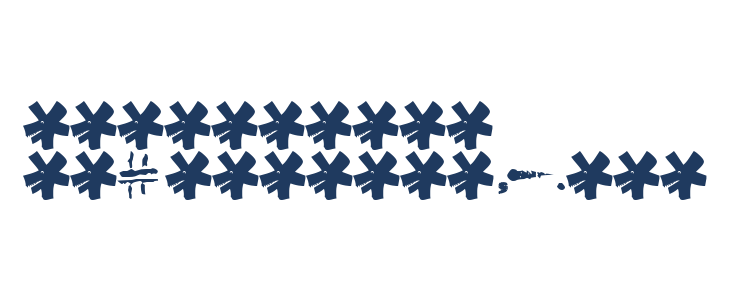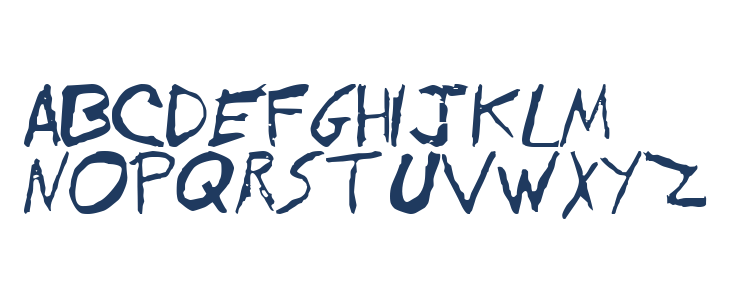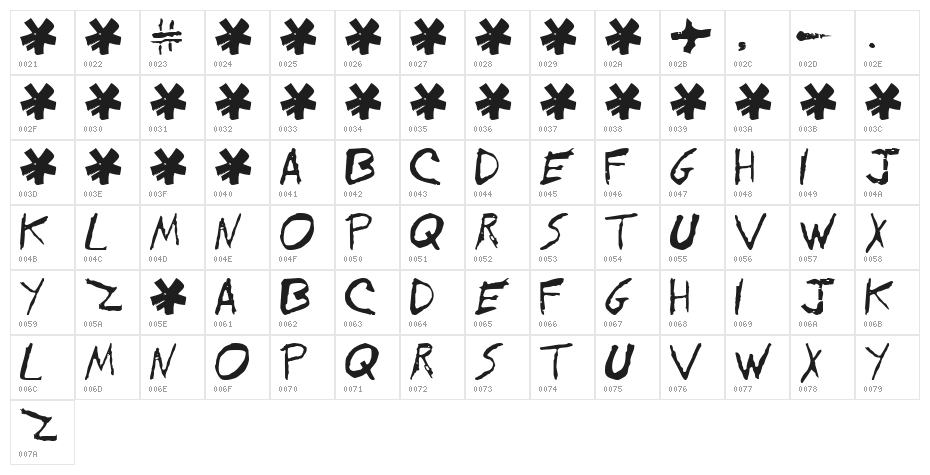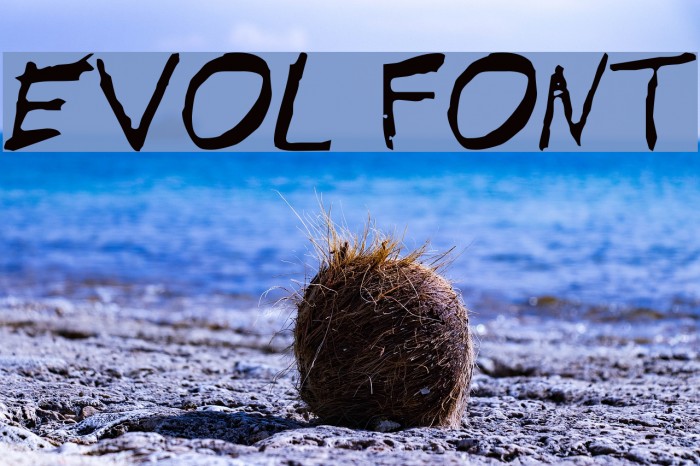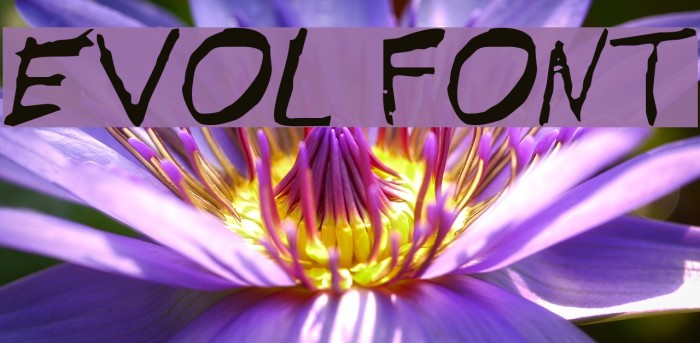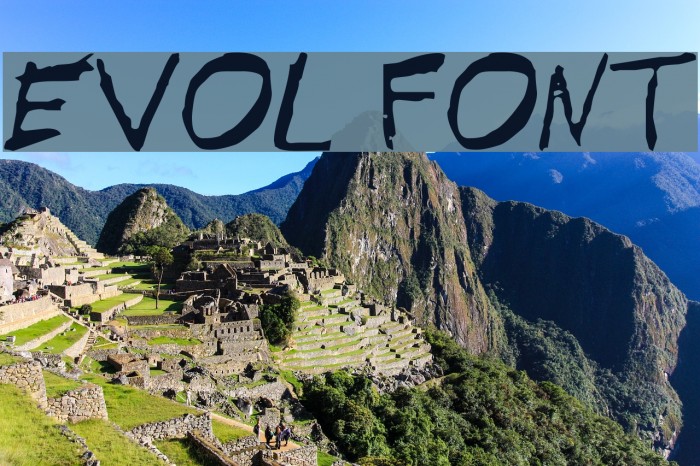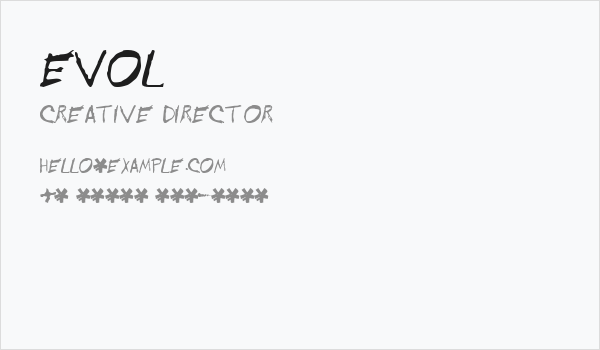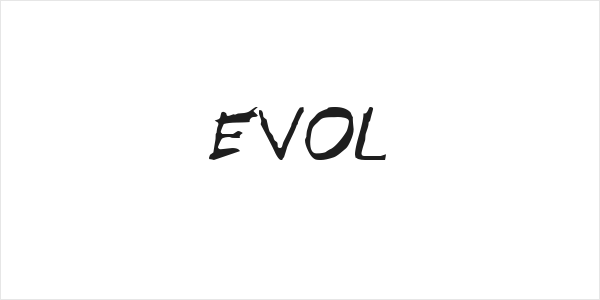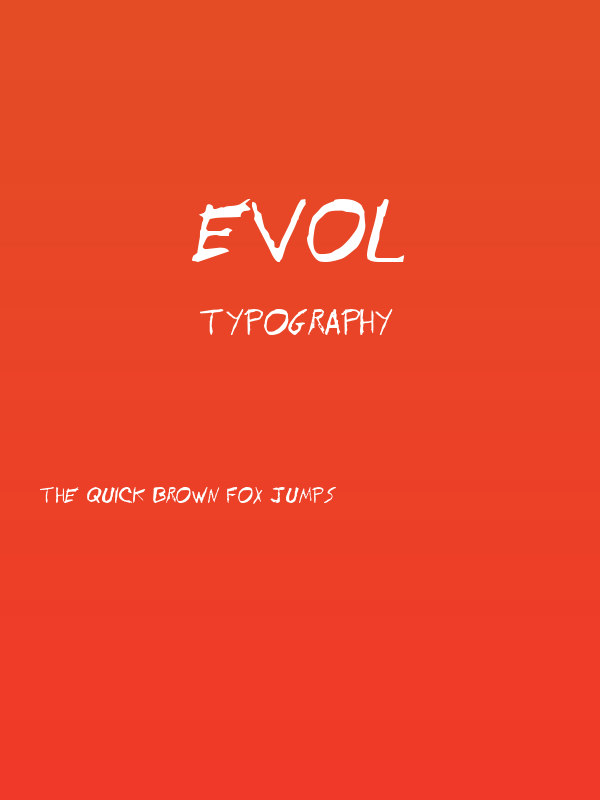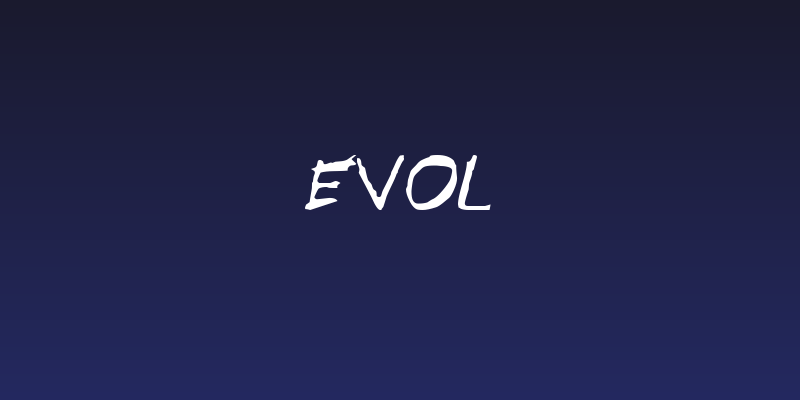
EVOL Font
| Versione | Version Based on SONIC YOUTH'S "EVOL" album cover. |
| Stile generale | Modern, Artistic |
| Progetti proposti | Ideal for posters, album covers, graffiti art, and edgy branding projects. |